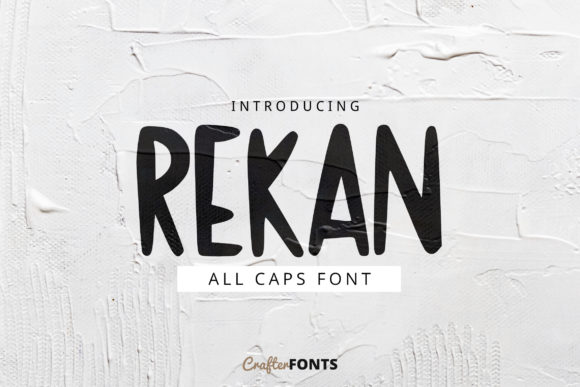
Rekan Display Font
Trouver les bons éléments de conception peut être un défi, mais Rekan Display Font propose une collection exceptionnelle qui rehausse instantanément votre travail.
Que vous créiez des produits POD (impression à la demande), des invitations de mariage ou des visuels pour les réseaux sociaux, Rekan Display Font est un choix idéal.